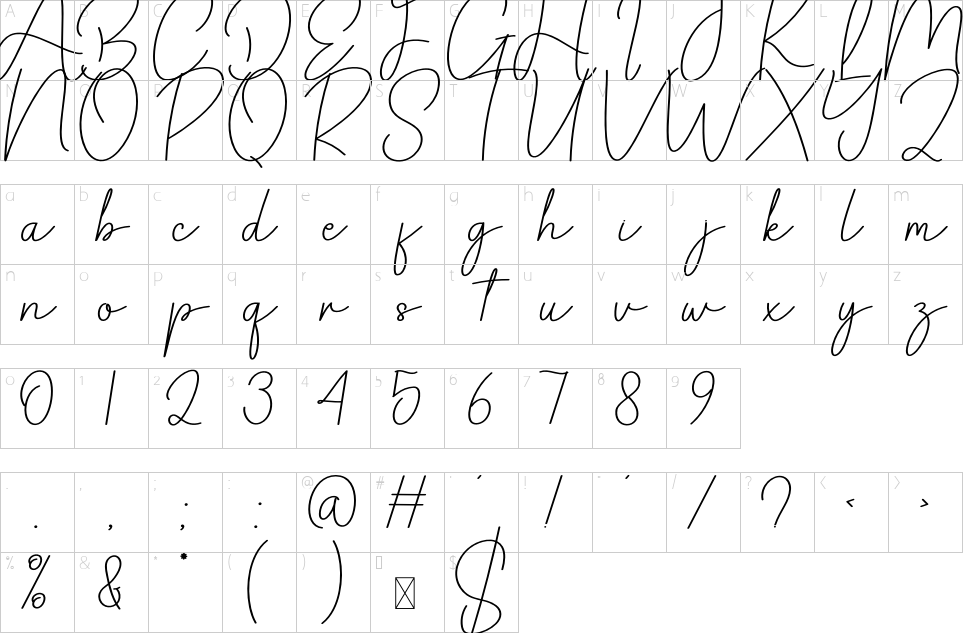
Angelica Signature Font – Fonte Grátis
Angelica Signature Font
Descubra a delicadeza e a elegância da Angelica Signature font, perfeita para estilos de design gráfico que valorizam a autenticidade. Esta fonte foi criada por scratchones, e já teve 387 downloads. Com traços finos e sutis, Angelica Signature é perfeita para criar efeitos gráficos que expressam confiança e sofisticação. Seja você um designer de web, um editor de imagens ou um gráfico em 2D, esta fonte pode se tornar seu parceiro de trabalho favorito, ajudando você a criar mensagens poderosas e visuais impactantes. Se você busca uma fonte elegante e minimalista, a Angelica Signature é uma escolha excepcional.
Mapa de caracteres da fonte Angelica Signature Font